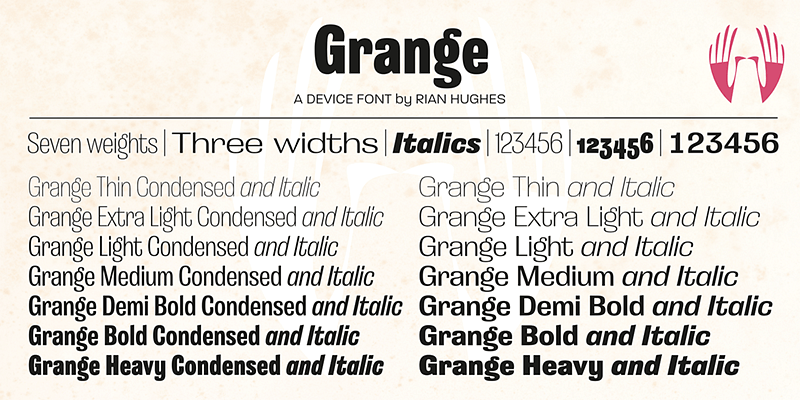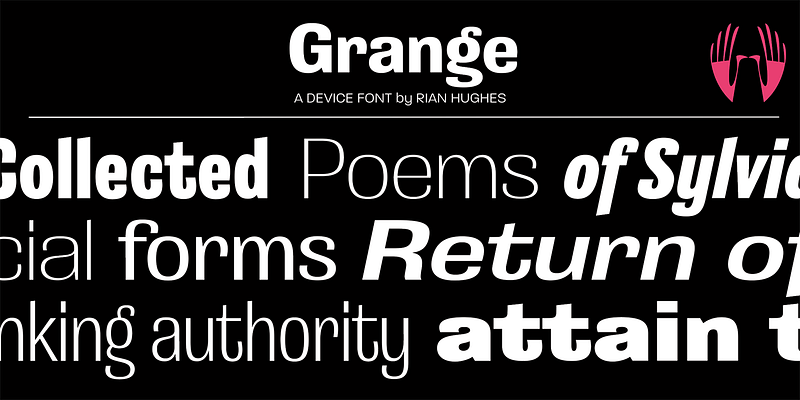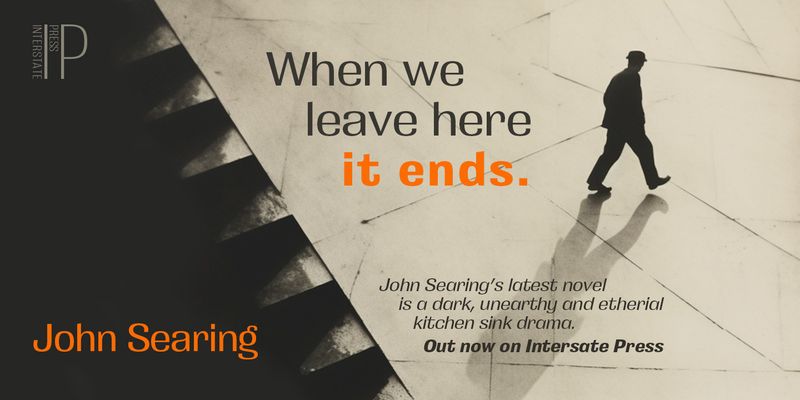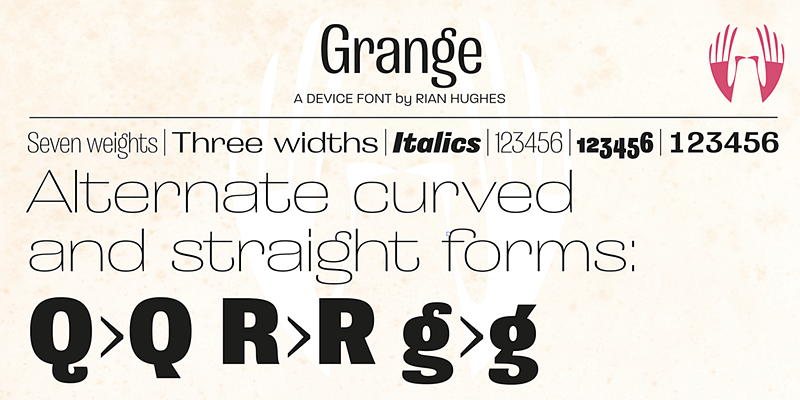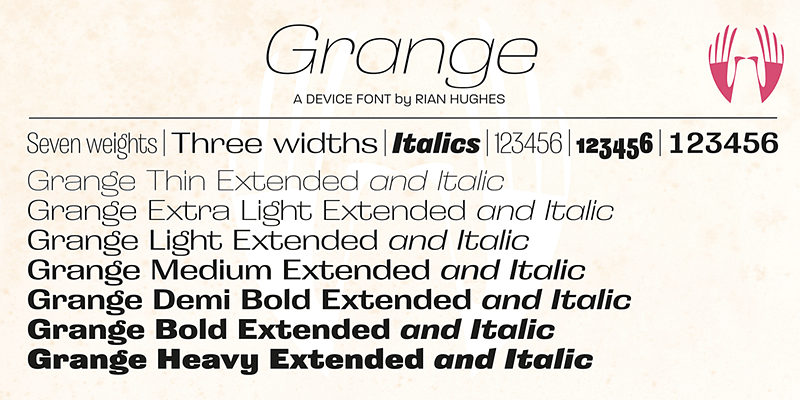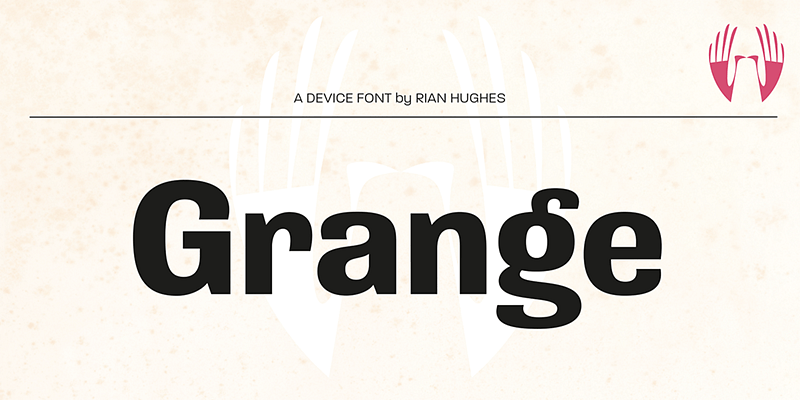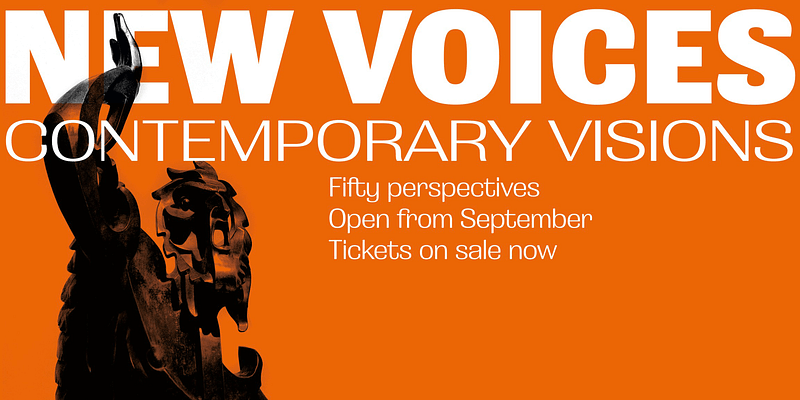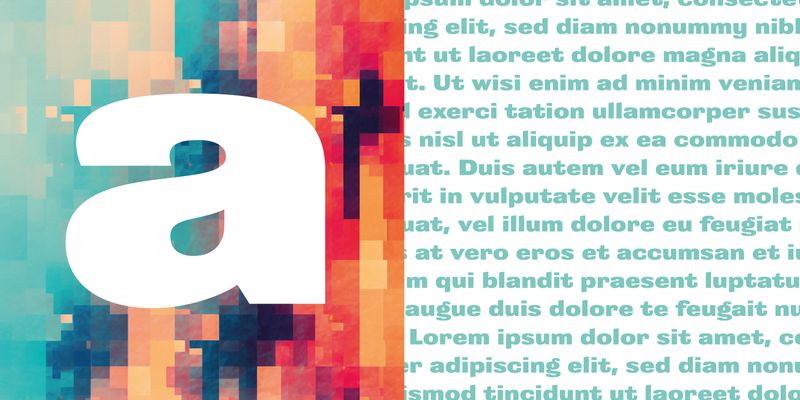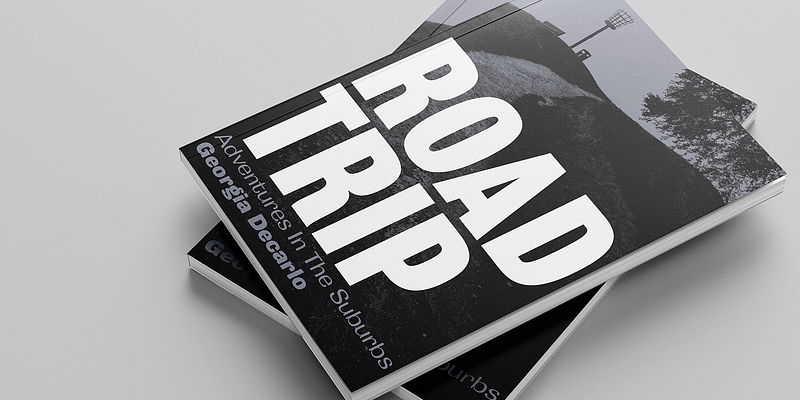
Una famiglia ampia e versatile di sette spessori e tre larghezze, più corsivo. Adatta per testo e titolo. Include figure vecchio stile e tabulari.
Caratteri, design e immagini a cura dell’illustratore e tipografo inglese Rian Hughes.